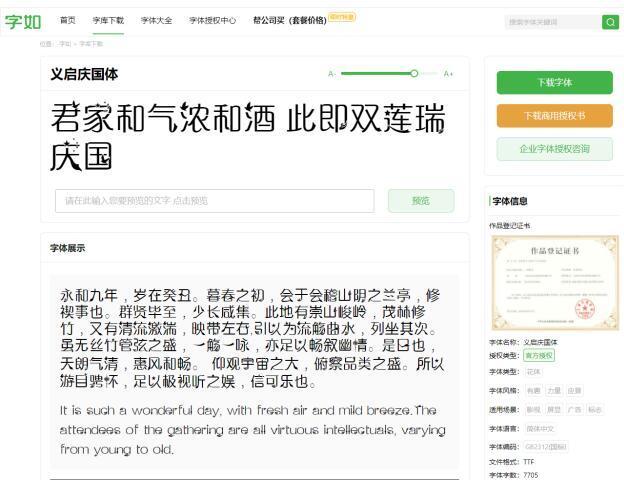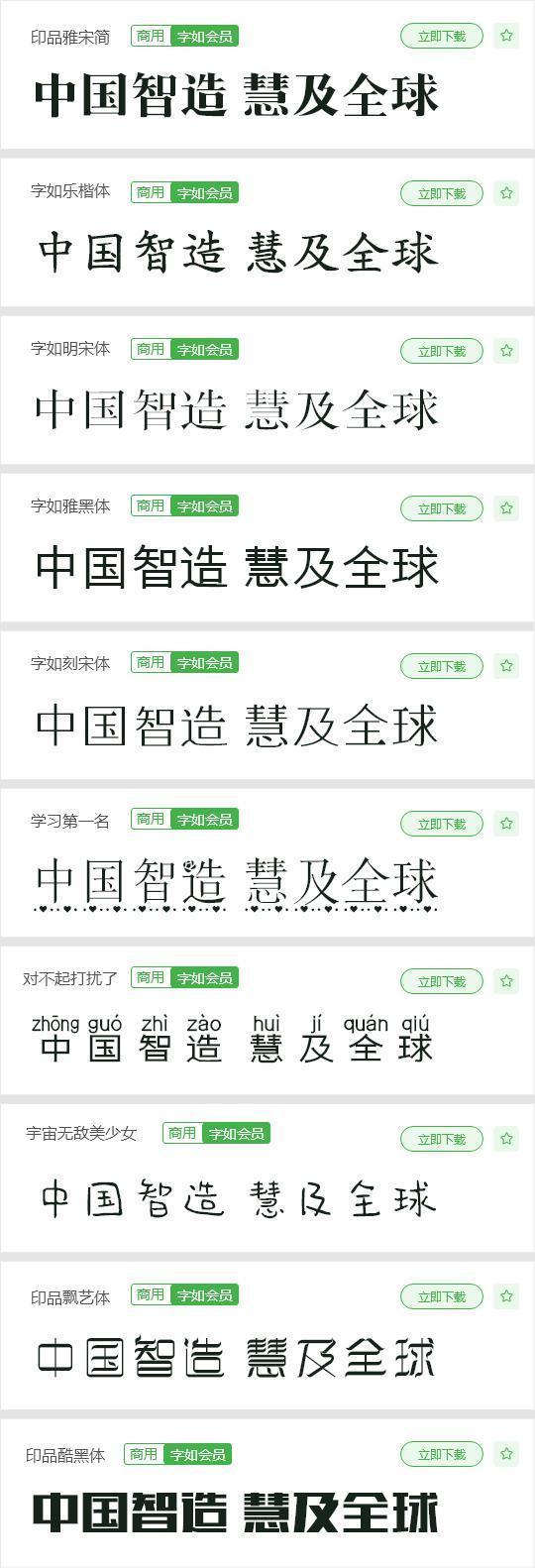
字体平台设计师悄悄收藏的字体网站
当今互联网技术可以下载到的可用的字体样式各式各样,有笔写有标准的字体样式,也是有独特的字体样式。应用字体样式时,要正确认识字体版权难题,看着你字体购买的地区是否靠谱方式,一些免费下载方式也是交费选购的,但并不是官网认证的方式,很可能便是不合理合法的。因此大伙儿依然在持续找寻各种各样可商业,无侵权行为风险性的字体,造型设计有特性的自主创新字体样式,让自身的內容写作提升大量优点,字如网的出現,毫无疑问协助了设计师们有了更多的选择。
字如网为大伙儿带来了各种丰富多彩的字体样式 ,除了目前市面上普遍的宋体字 、黑体字以外,颇有特色和艺术创意的字体样式是字如网一大特点。 这儿包括传统式墨笔书法艺术设计风格字体样式,也是有当代超可爱日系小清新的字体样式,乃至是圆体,也是有出现订制字体样式,自然设计师们要找的完全免费商用字体,在这个服务平台也是有,做为艺术创意者来讲,可挑选的范畴十分大。